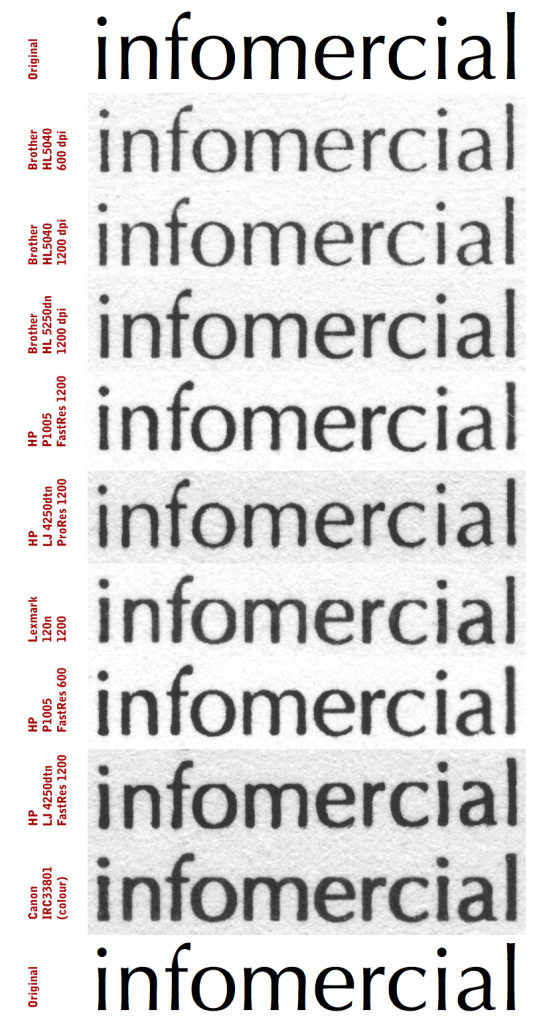
Laserdrucker für den Hausgebrauch & Schriftgestaltung
Ich spiel zur Zeit mit der Überlegung mir für den Hausgebrauch einen Laserdrucker anzuschaffen, da ich keine Lust mehr auf horrende Preise im Copyshop hab und mit dem Druckbild an meinem alten Tintenspritzer überhaupt nicht zufrieden bin. Im Studium hat er seine Dienste getan aber wenn ich mit dem Schriftzeichnen weitermachen will, komm ich auf kurz oder lang einfach nicht um dieses Thema herum.
Jetzt hab ich hier schon ein wenig rumgesucht und bin auf einen Kommentar von Dan gestoßen.
Mann braucht ein echtes PostScript Drucker wenn mann Text- oder andere kleine Schriften Testen will. Sonnst kriegts du (durch das Rasterizer oder durch einfach schlechte Druckqualität) ein falsches Schriftbild. Für "normale" Designer ist dieses falsches Schriftbild völlig OK. Aber für Schriftdesigner den Tod. Mann muß wissen, wie die Schriften tatsächlich aussehen, oder?
Mann braucht ein echtes PostScript Drucker also, wenn mann mit echten PostScript Kurven zeichnet!
Wie sieht es denn mittlerweile aus, hat sich dort was geändert da ich nicht wirklich das Geld hab und um 700-800 Euro für den Hausgebrauch ausgeben kann, nur weil ich den Grauwert und alles was dazu gehört kontrollieren will. Wenn es halt in der Preiskategorie bleibt, heißt es erstmal sparen und weiter zum Copyshop gehen.
Es gibt mittlerweile echt gute Angebote, die Testbericht zeigen das auch aber nützt mir das als Schriftgestalter das irgendwas.
Einen ersten Überblick erhältst du hier
Der HP 2050 ist im Übrigen mit PS3-Emulation ausgestattet und kostet um die 200 Euro …
Das Thema hatten wir letztens auch in unserem Type Design Nachdiplomstudium. Unser Dozent hat uns die Brother-Laser-Drucker wärmstens empfohlen. Irgendwo habe ich noch ein Bild von einem Druckvergleich wie Schrift auf verschiedenen Postscript-Druckern aussieht – mal sehen ob ich das Bild noch finde ... mach mich mal auf die Suche
Emulation heißt in diesem Fall dass da kein original Adobe Postscript verbaut ist sondern eine in Lizenz hergestellte Postscript-Lösung. Die aber genau so gut oder schlecht wie das Original ist, da es technisch gesehen keine Unterschiede gibt.
Das Thema mit den Emulationen hatten wir kürzlich schon mal:
Ich hab die Erfahrung gemacht, dass Angaben wie «PS-Emulation» oft nicht sehr verlässlich sind (bzgl., ob es denn nun eine Emulation oder echtes PS ist), das können einem z.T. nicht mal die Kundenberater sagen… :x
Das Thema hatten wir letztens auch in unserem Type Design Nachdiplomstudium. Unser Dozent hat uns die Brother-Laser-Drucker wärmstens empfohlen. Irgendwo habe ich noch ein Bild von einem Druckvergleich wie Schrift auf verschiedenen Postscript-Druckern aussieht – mal sehen ob ich das Bild noch finde ... mach mich mal auf die Suche
So, musste meinen Studienkollegen fragen, ob ich das Bild auch posten darf.
Er wollte sich einen geeigneten Drucker für Type Design zulegen, wusste aber nicht, welcher sich am besten dafür eignen würde. Im Fachgeschäft konnten sie ihm auch nicht weiterhelfen. Also hat er seine Kumpels gebeten, auf ihren Druckern Optima in 6 Punkt ausdrucken. Er hat das ganze dann mit 1200dpi eingescannt. Lange Rede kurzer Sinn – hier sein Resultat:
Wow ... Da gewinnt bei mir ganz knapp Nummer 2 vor 3 aber nur weil die Querstriche mir ein klein wenig zu dunkel vorkommen.
Das heißt man sollte sich um den Brother HL 5250dn bemühen?
... den es für nur 250 Euro bei Amazon gibt?
Das geht jedenfall aus Richard's Test hervor. Vielleicht können wir diesen Test hier im Forum ausbauen – ich könnte dazu ein geeignetes PDF zusammenstellen. :?
es bleibt natürlich die Frage ob die Kumpels immer die bestmögliche Einstellung für Schriftgestaltung bei ihrem Drucker gewählt haben ...
Welches wären denn die besten Einstellungen für Type Design Deines Erachtens? :?
Einfach die bestmögliche die der jeweilige Drucker schafft.
Zum Beispiel kann der Brother offenbar zwei Druckersprachen, PCL6 und eine (eigenentwickelte?) Postscript3-Emulation. Je nachdem könnte was anderes rauskommen.
Oder: Deformiert der HP 4250 die Buchstaben wirklich immer so extrem oder gibt es vielleicht eine Treibereinstellung die das besser kann?
Ich find die Aktion super, das ist das erste mal dass ich sagen kann "Drucker XY überzeugt mich für meinen Anwendungsfall.", das ist ja schon mal super, denn bisher war ich immer recht ratlos bei Druckertests ... Aber ich weiß nicht, ob das ein anderer nicht auch könnte, je nachdem wie er eingestellt ist, denn unser Büro-Raumschiff liefert auch je nach Einstellung von ganz schrecklich bis ziemlich beeindruckend alles ...
Das heißt man sollte sich um den Brother HL 5250dn bemühen?
... den es für nur 250 Euro bei Amazon gibt?
Man liest viel Unschönes darüber: :evil:
Wie wissenschaftlich das ganze ist, weiß ich auch nicht. Im Netz findest Du zu den jeweiligen Druckern passende Filter, die den Tonerstaub rausfiltern sollen. Ob's was bringt weiß der Teufel :?